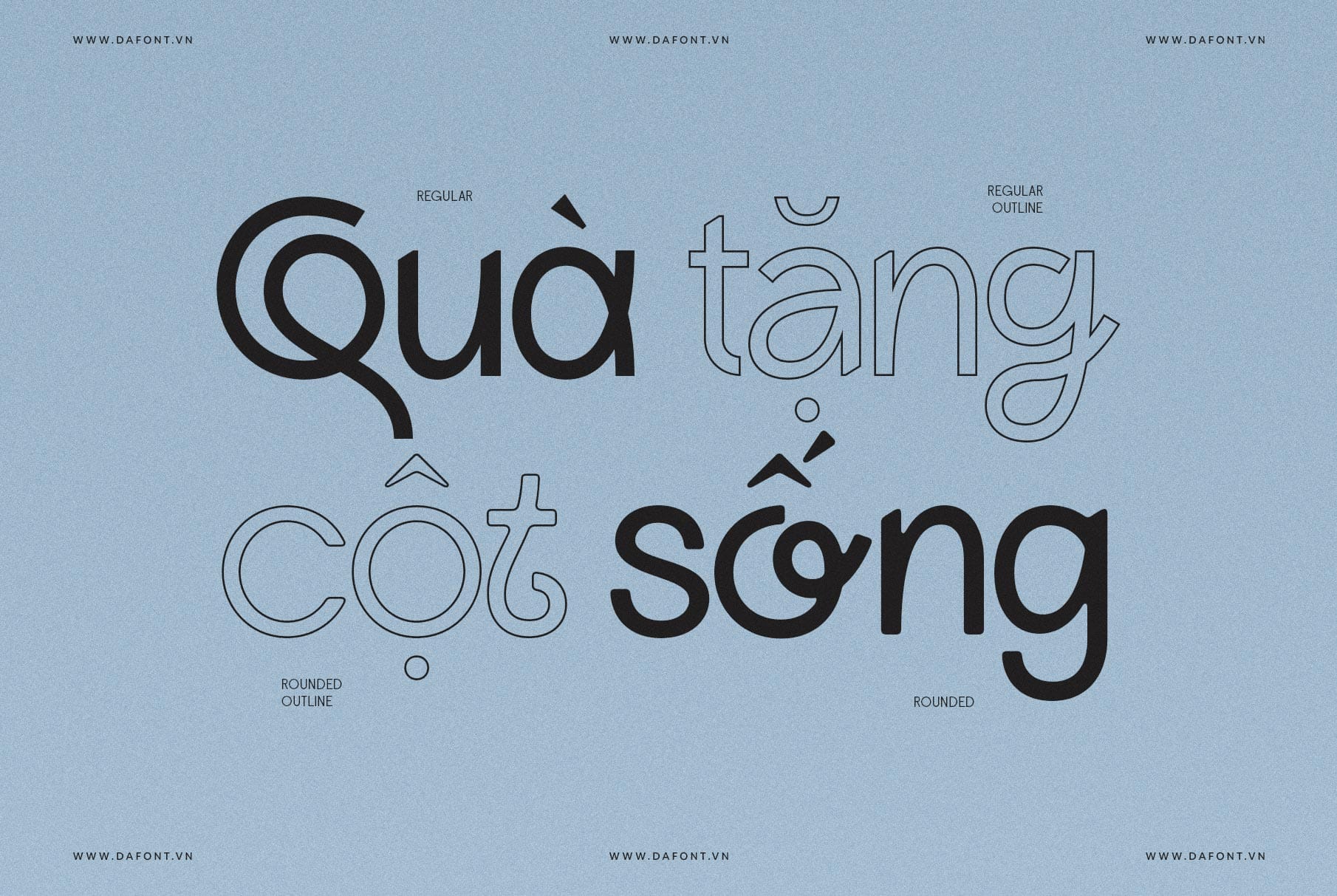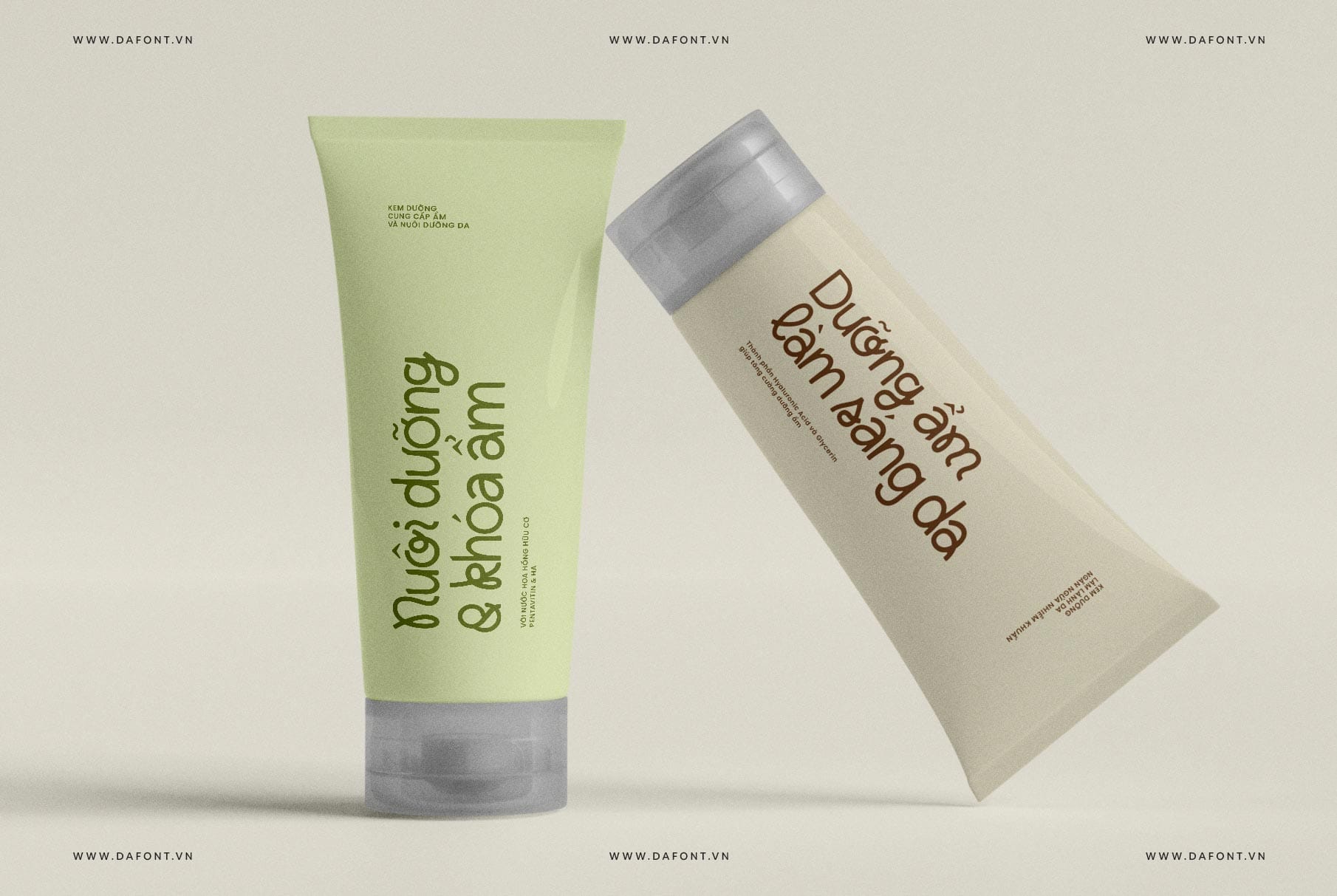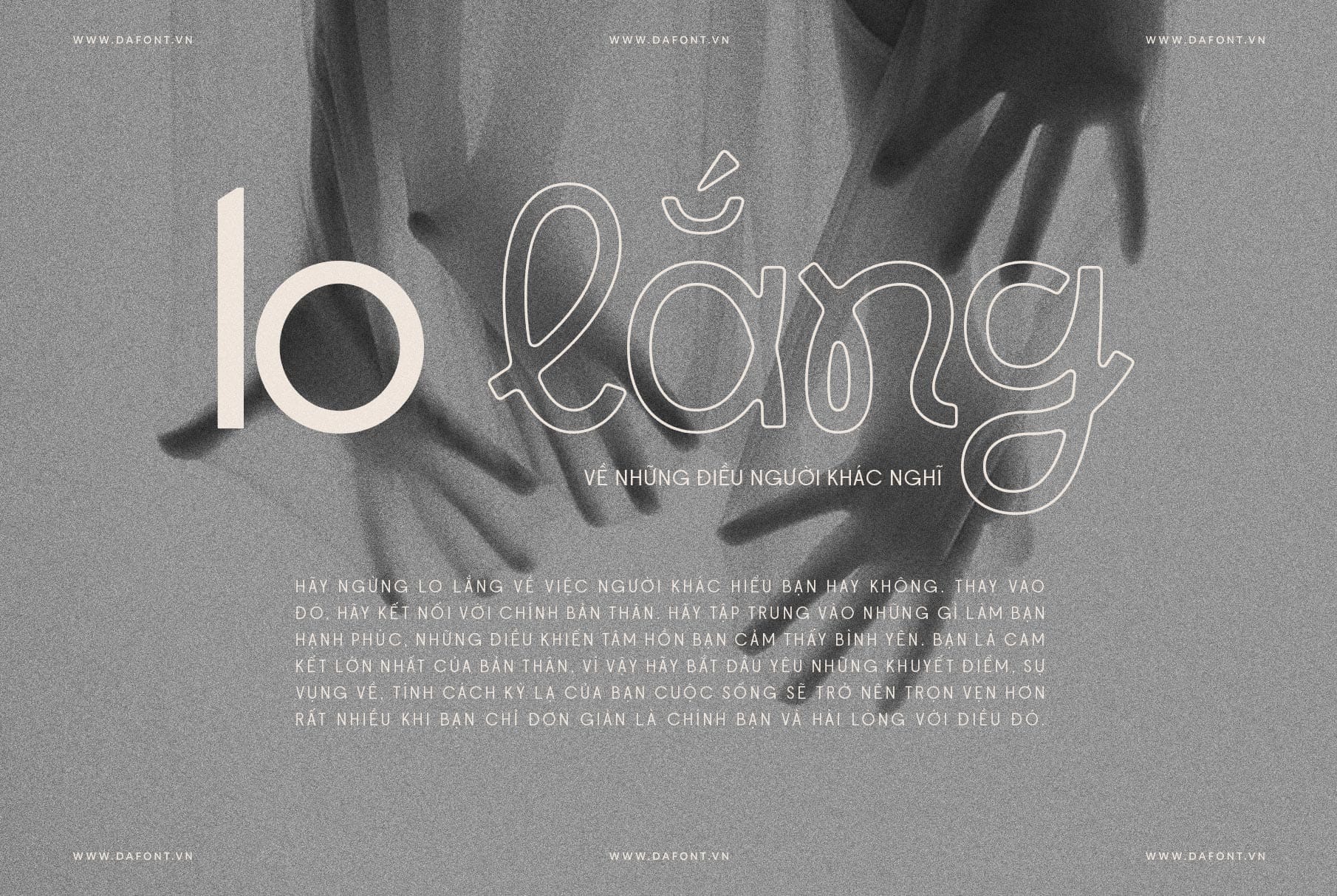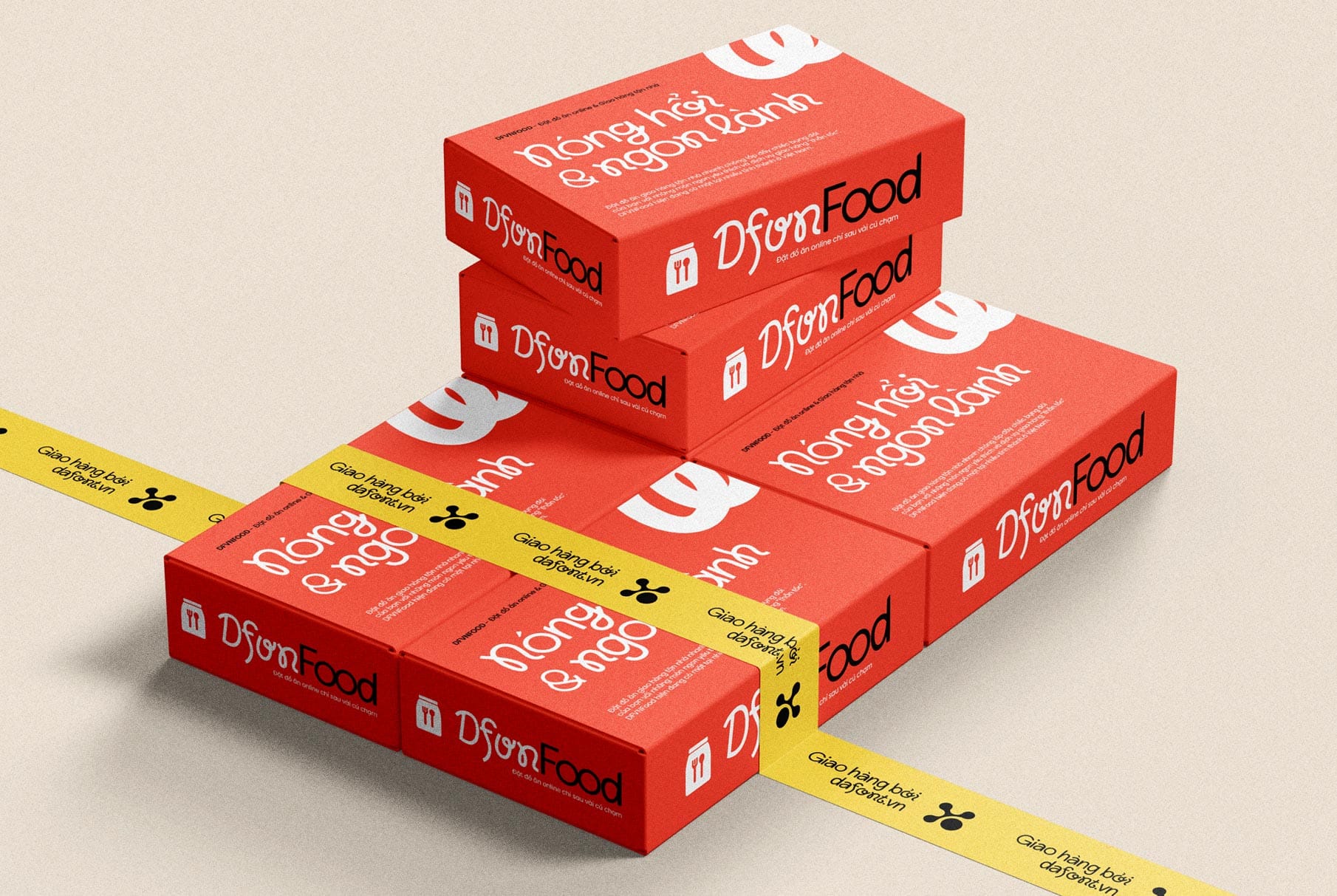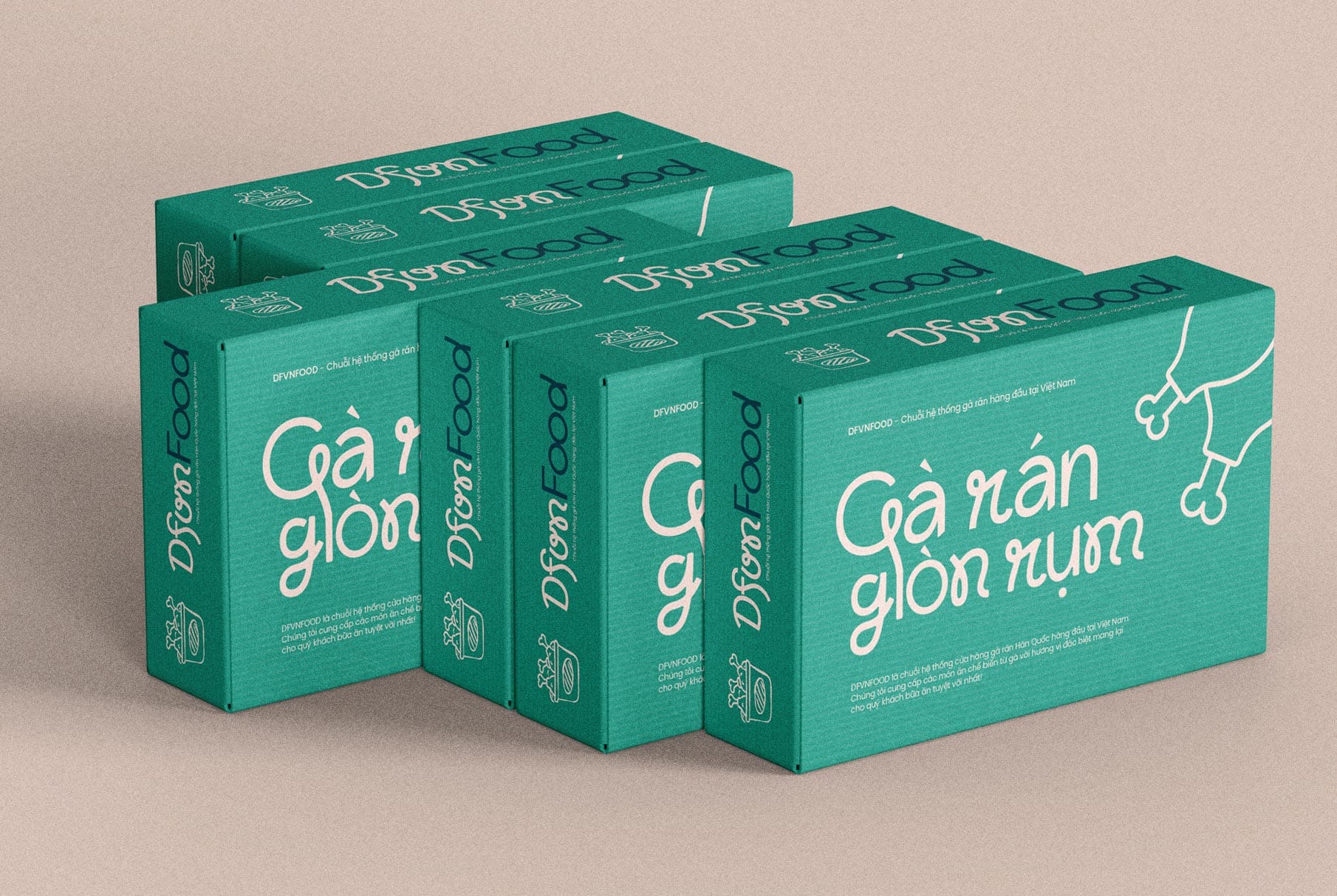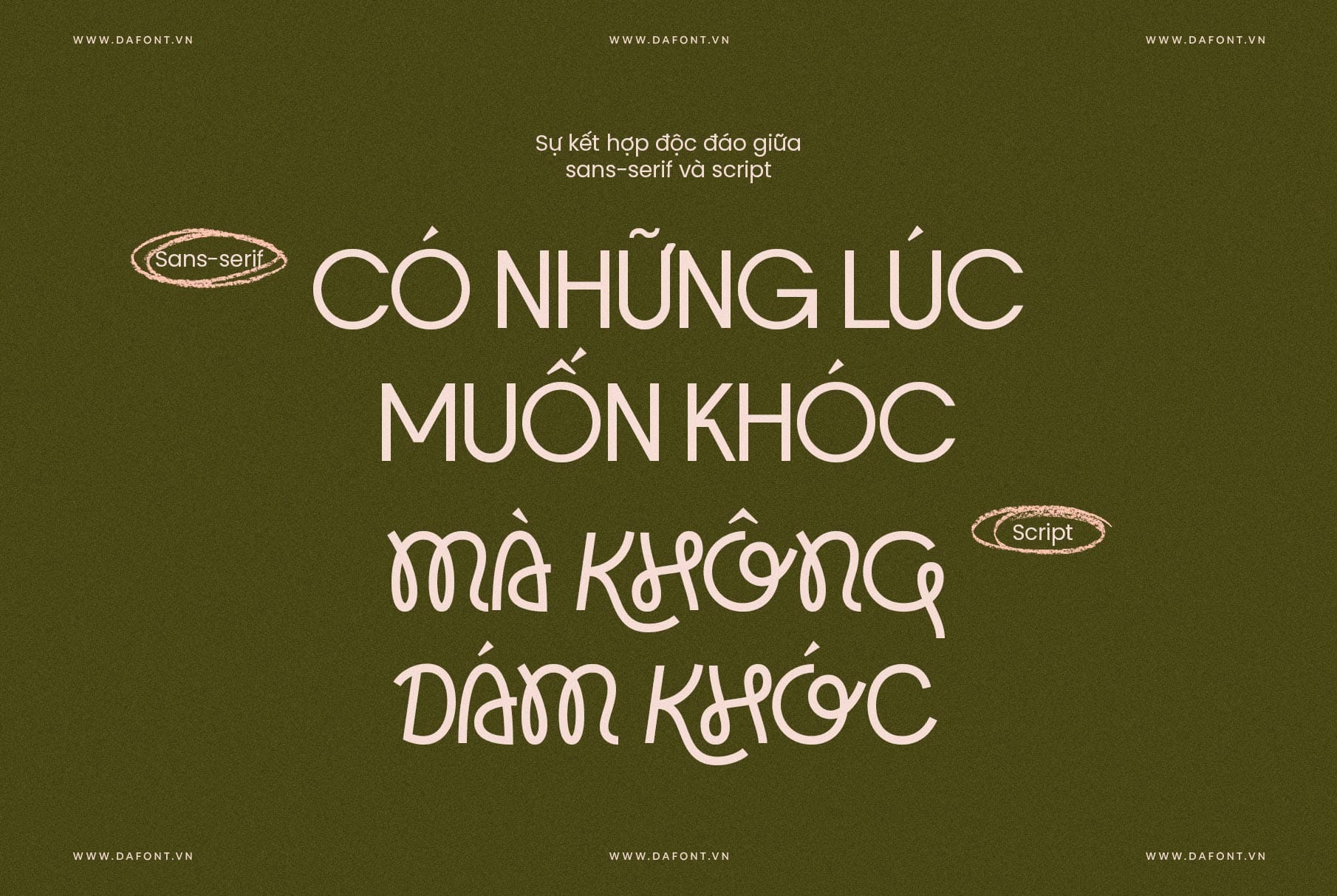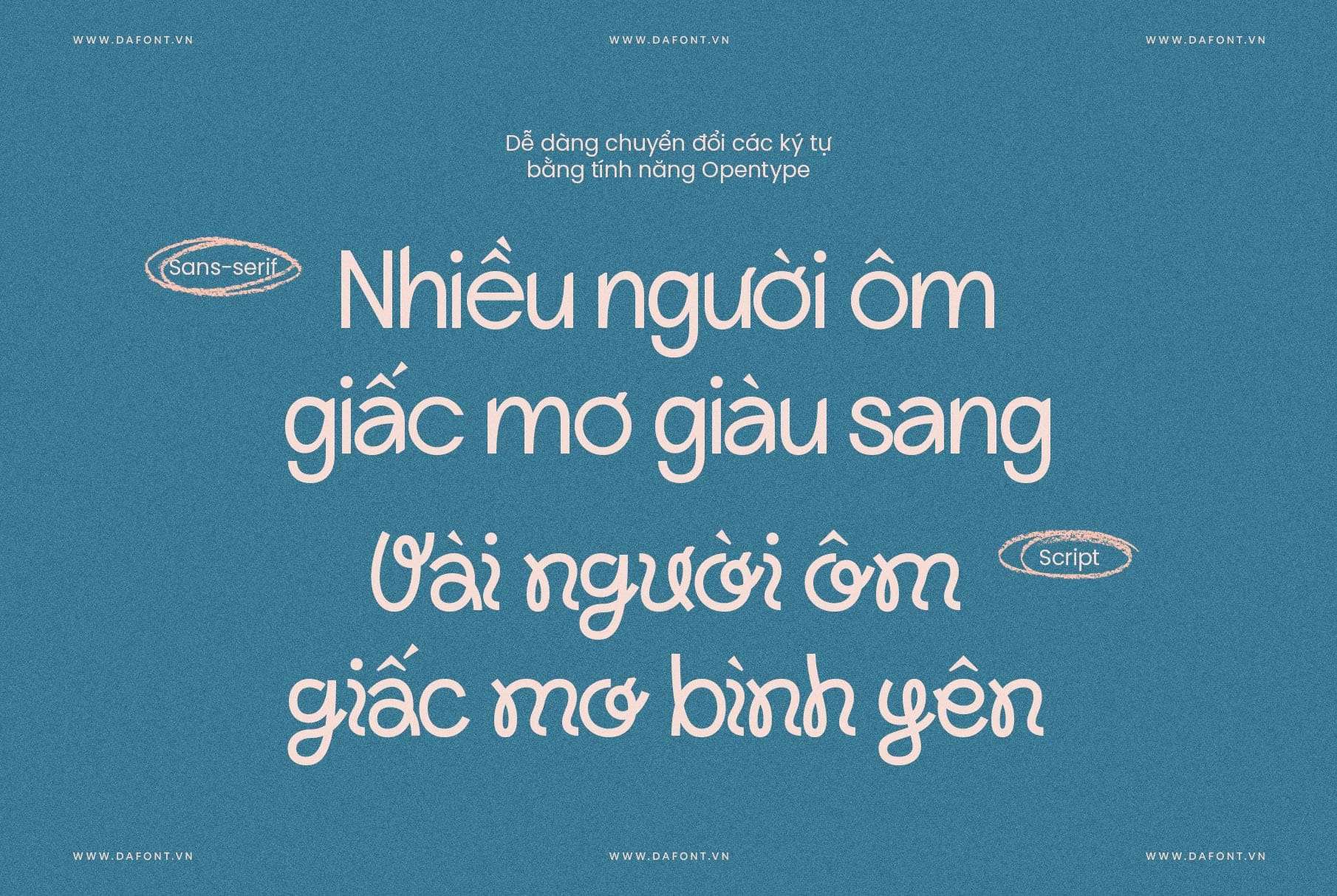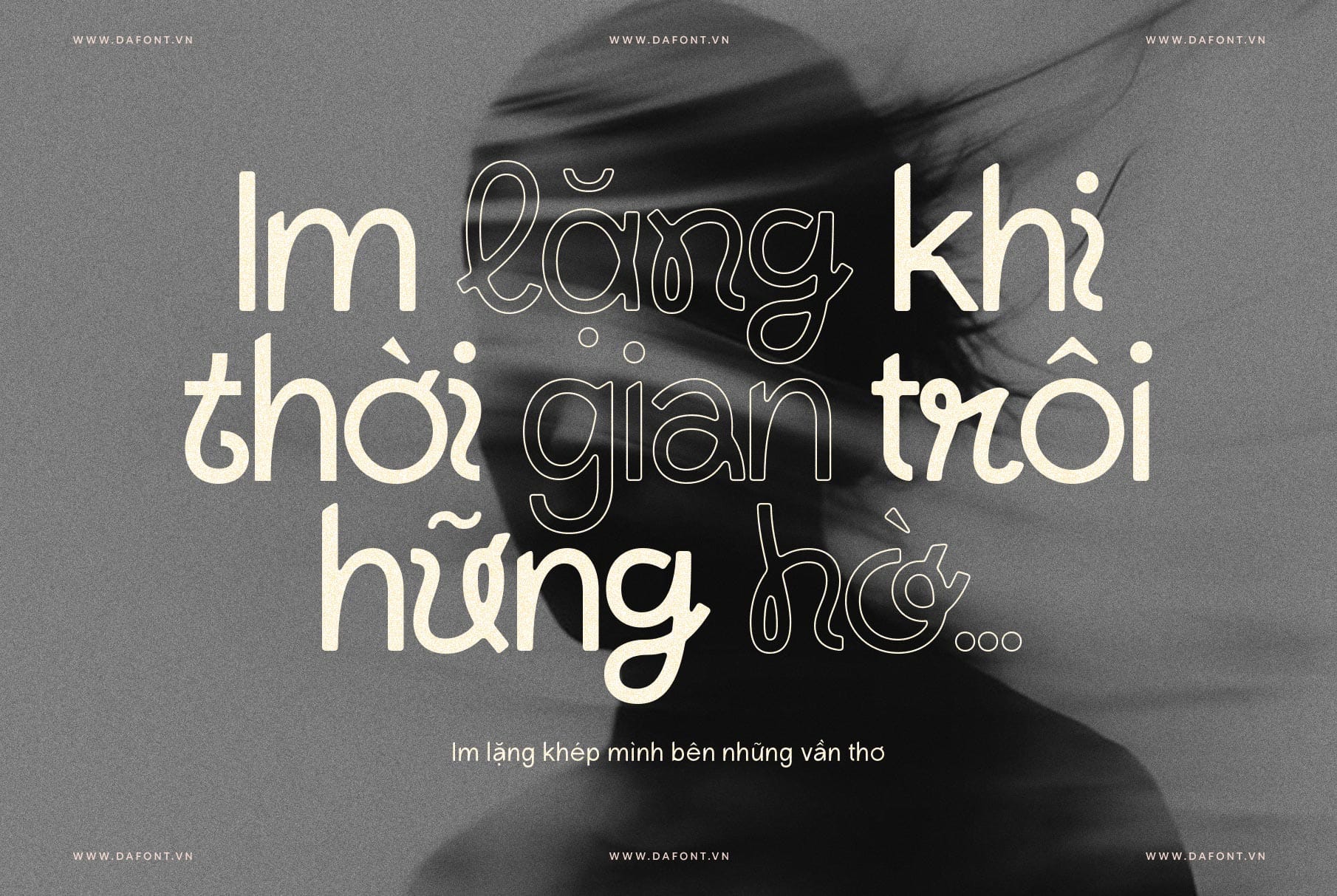
DFVN Lightshift
Làm nổi bật thiết kế với phong cách phá cách
DFVN Lightshift là một font chữ hiển thị (display font) đậm chất vui nhộn, năng động và đẹp mắt. Với sự kết hợp giữa đường nét đơn giản của sans-serif và sự bay bổng của script, Lightshift là sự hòa quyện hoàn hảo giữa hiện đại và sáng tạo, mang lại nét cá tính độc đáo cho mọi dự án.
Đặc điểm nổi bật của DFVN Lightshift
Lightshift font là một font chữ độc đáo, thường được ưa chuộng trong các thiết kế sáng tạo nhờ các đặc điểm nổi bật sau:
1. 4 font độc đáo: Lightshift cung cấp 4 biến thể gồm Regular, Outline, Round và Round Outline. Mỗi phong cách mang đến một hương vị riêng biệt, phù hợp cho nhiều ngữ cảnh sáng tạo.
2. Hơn 200 ký tự thay thế và chữ ghép được Việt hóa: Bộ sưu tập ký tự thay thế phong phú và ligature đồ sộ của Lightshift cho phép người dùng tạo ra những hình thức chữ độc đáo, tất cả đều được Việt hóa và dễ dàng sử dụng.
3. Hiện đại và đẹp mắt: Những đường cong mềm mài và đường nét dày của Lightshift gợi lên cảm giác năng động, vui nhộn và trẻ trung.
4. Ứng dụng linh hoạt: Lightshift phù hợp cho nhiều bối cảnh thiết kế như logo, tiêu đề, đồ họa mạng xã hội, bao bì sản phẩm và nhiều hơn nữa.
DFVN Lightshift phù hợp nhiều thiết kế khác nhau
Lightshift là lựa chọn hoàn hảo cho các thương hiệu trẻ trung, các nhà thiết kế đồ họa, và bất kỳ ai tìm kiếm một font chữ với phong cách phá cách, năng động cho dự án của họ.
Ứng dụng tuyệt vời trong:
• Xây dựng thương hiệu trẻ trung và hiện đại
• Thiết kế poster, tờ rơi và tài liệu quảng cáo
• Tiêu đề website và đồ họa mạng xã hội
• Bao bì sản phẩm và tiếp thị
Kết luận
DFVN Lightshift bao gồm 4 font được Việt hóa tỉ mỉ, với kerning được tinh chỉnh toàn diện cho mọi ký tự, bao gồm cả các ký tự thay thế. Hệ thống dấu được tối ưu hóa, đồng thời tích hợp đầy đủ các tính năng OpenType, mang đến trải nghiệm sử dụng vượt trội.